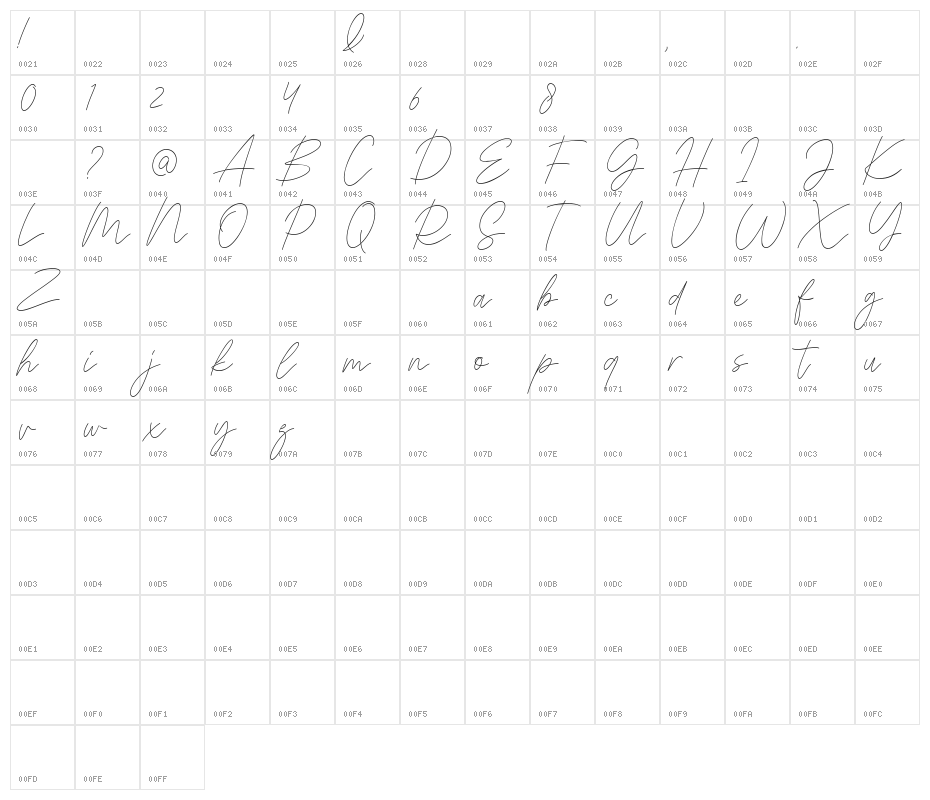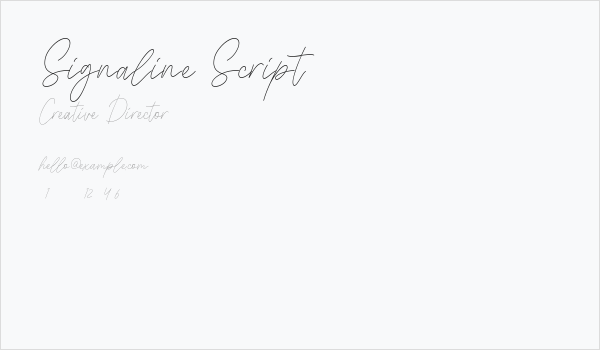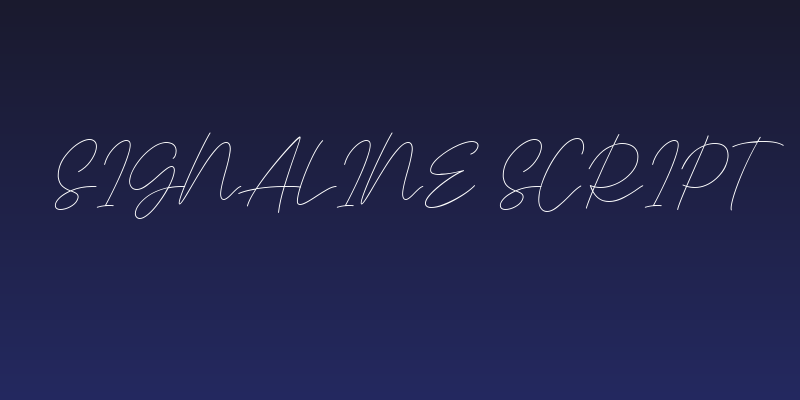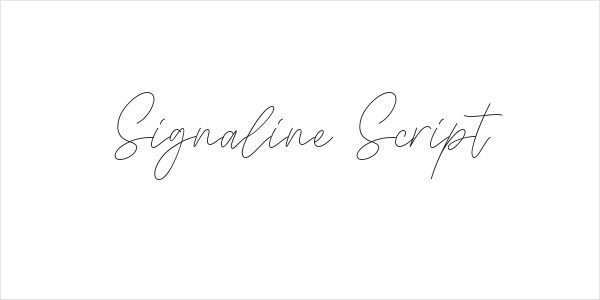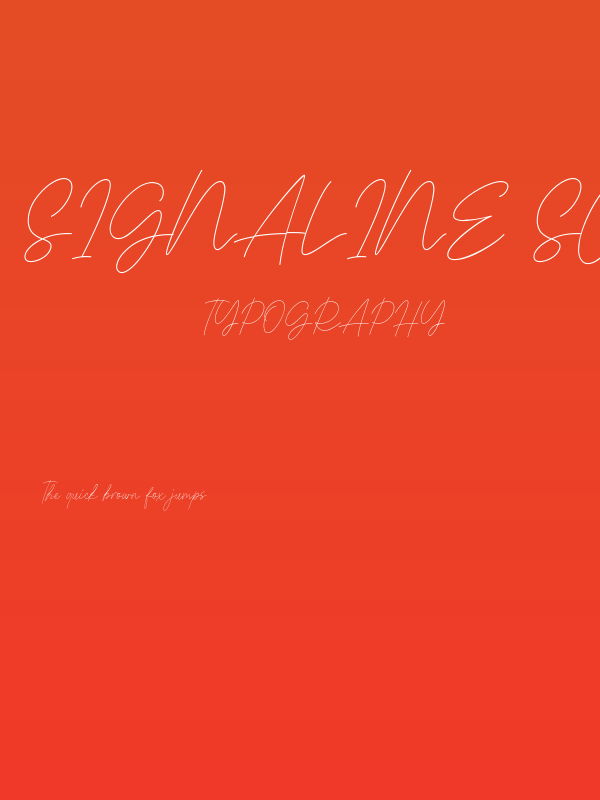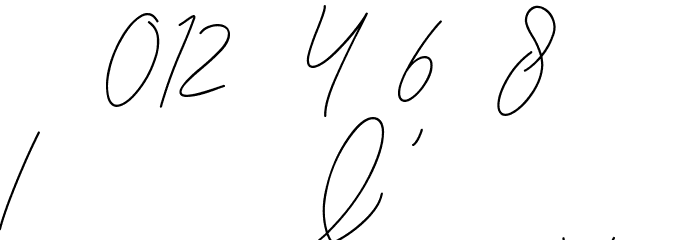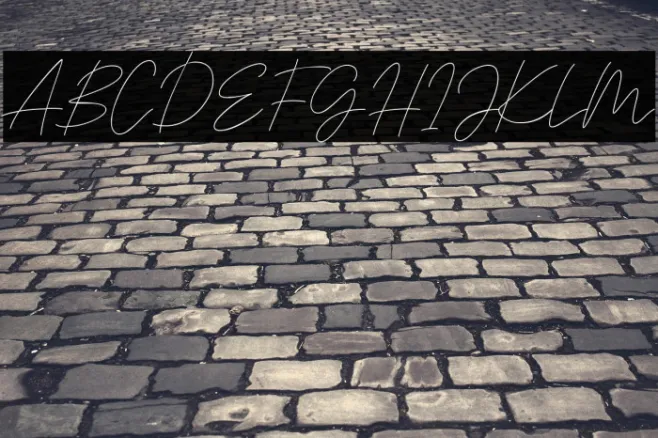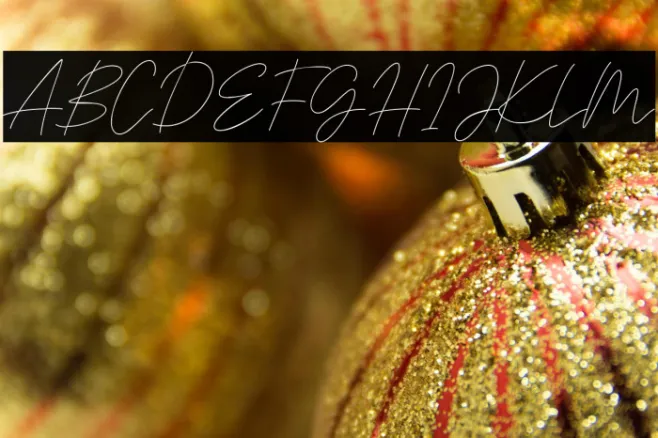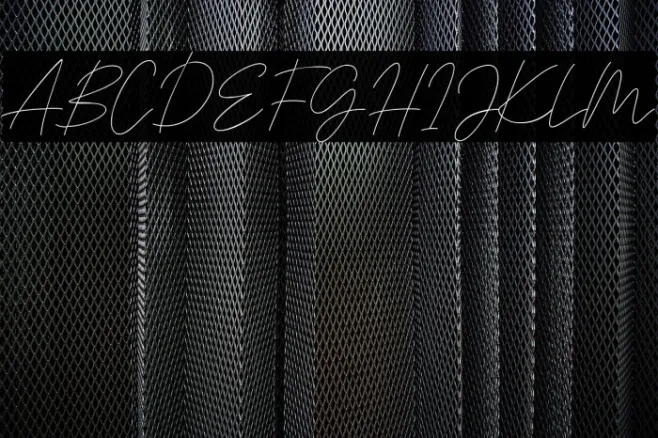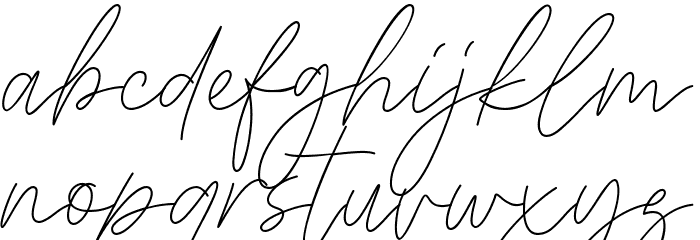
Signaline Script Font
| Gesamtstil | Elegant, Handwritten |
| Anwendungsfall | Logos, Invitations, Artistic projects |
| Vorgeschlagene Projekte | Ideal for wedding invitations, greeting cards, personal branding, and artistic projects requiring a handwritten touch. |